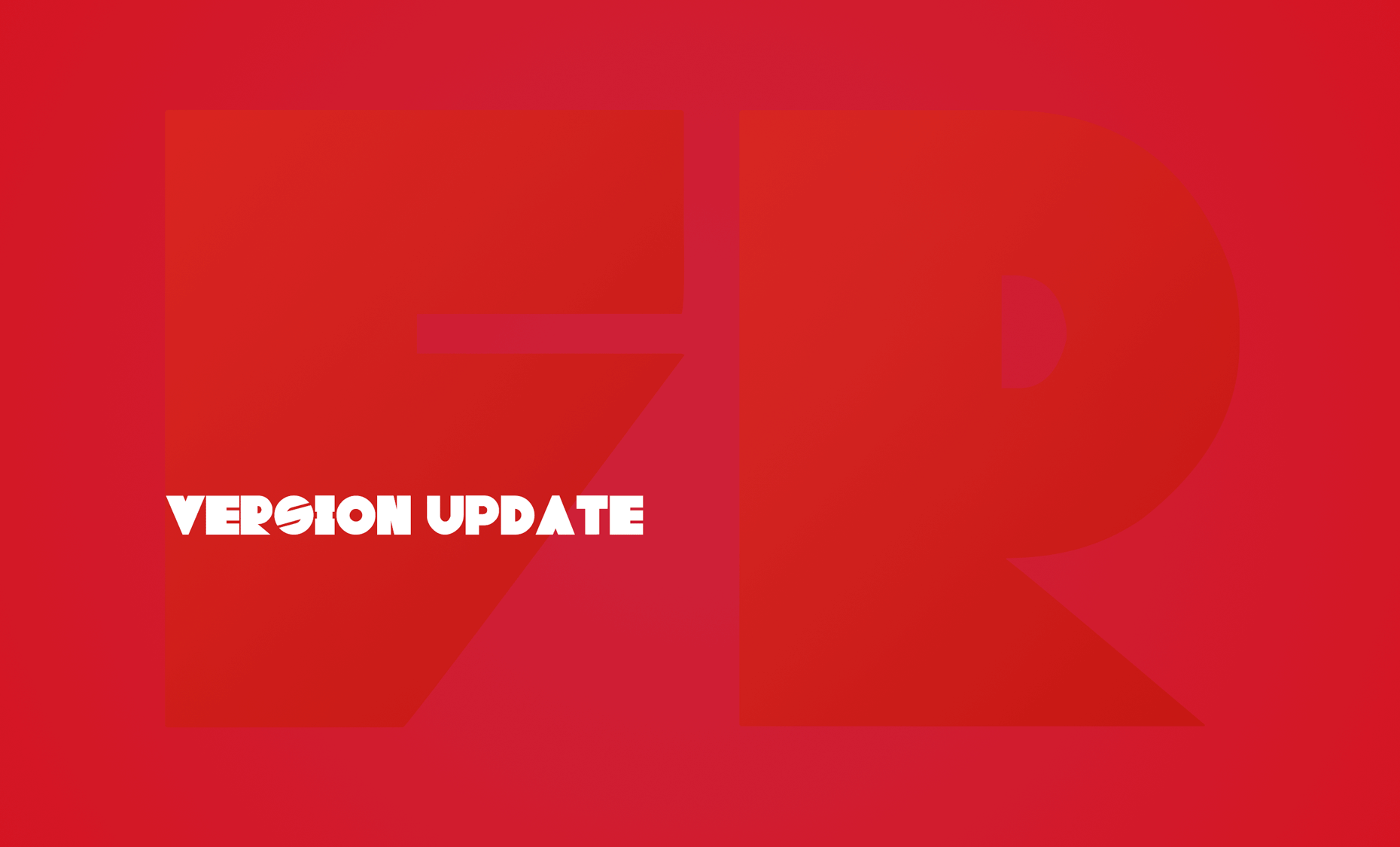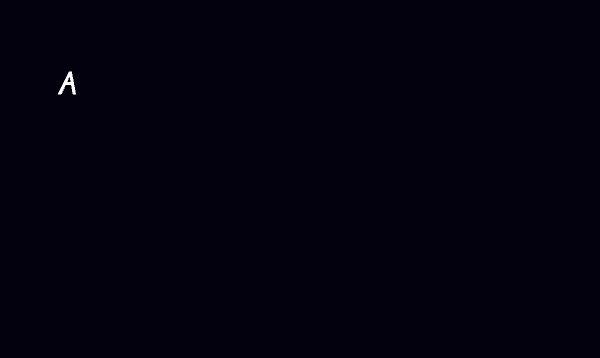
homework英文字库 免费商用
半个月前新媒体课上脑抽突然想做自己的个人字库,通过各种渠道了解方法、查教程;教程虽没找到多少但是自己熬夜琢磨出来了。可把自己惊呆了。过两天就考试了,得远离设计好好复习一波,挂科是我不可承受之重。
我在做完字体framework后,身边不少朋友嫌弃使用场景太少,不实用(小声哔哔:那是你不会用,hhh);我怎么能忍受这种不负责的话呢,所以我不仅改良了framework还又做了一套字体homework,灵感嘛来源于小时候作业本上的英文单词和句子,还记得那首“拼音字母歌”,“abcdefg hejklmn opq rst uvw xyz”旋律依旧熟悉难忘。
那时放学就意味着一天“受罪”的结束,今后下班了还会有加班,希望急字体可以陪大伙一块放学,少加些班。